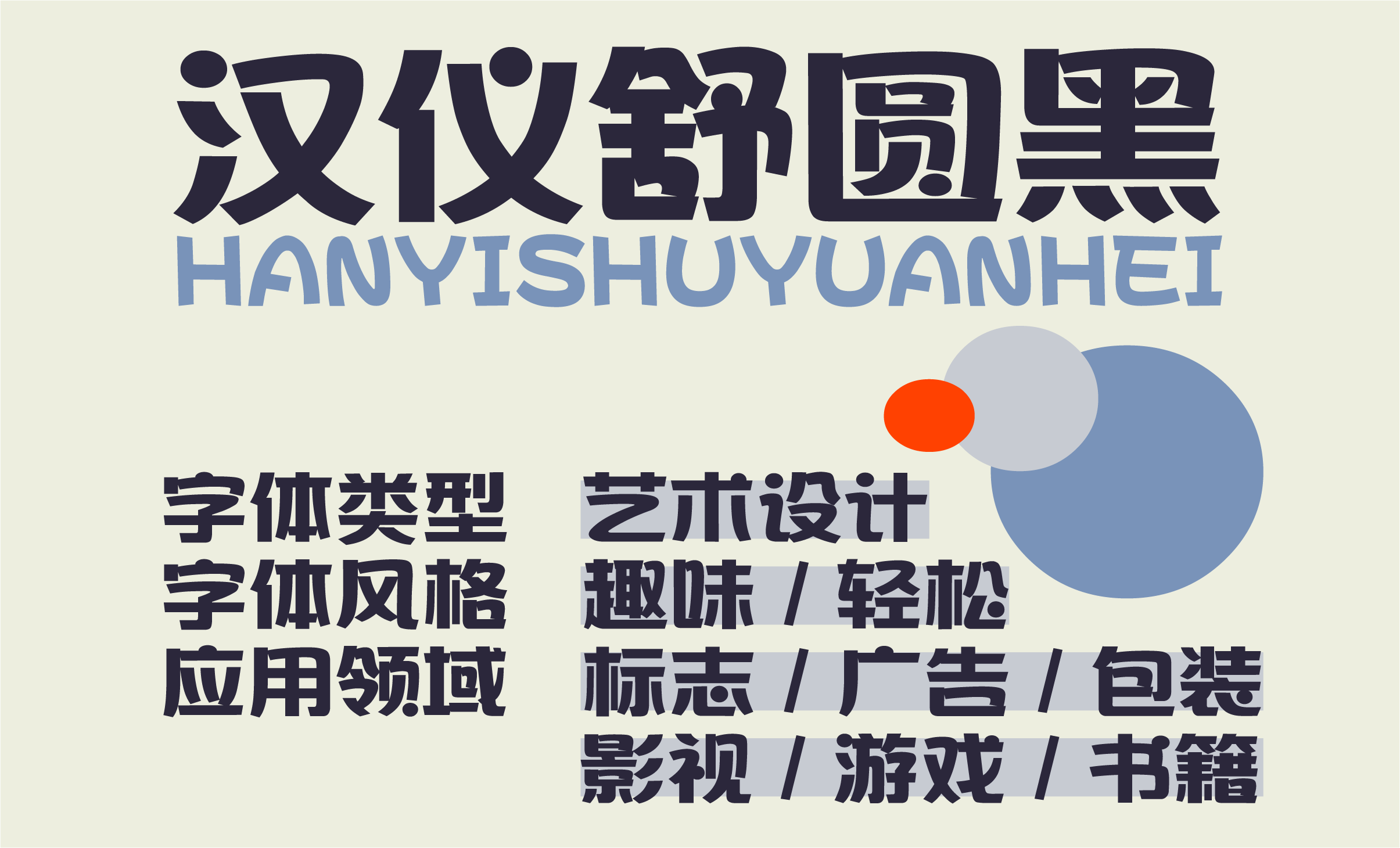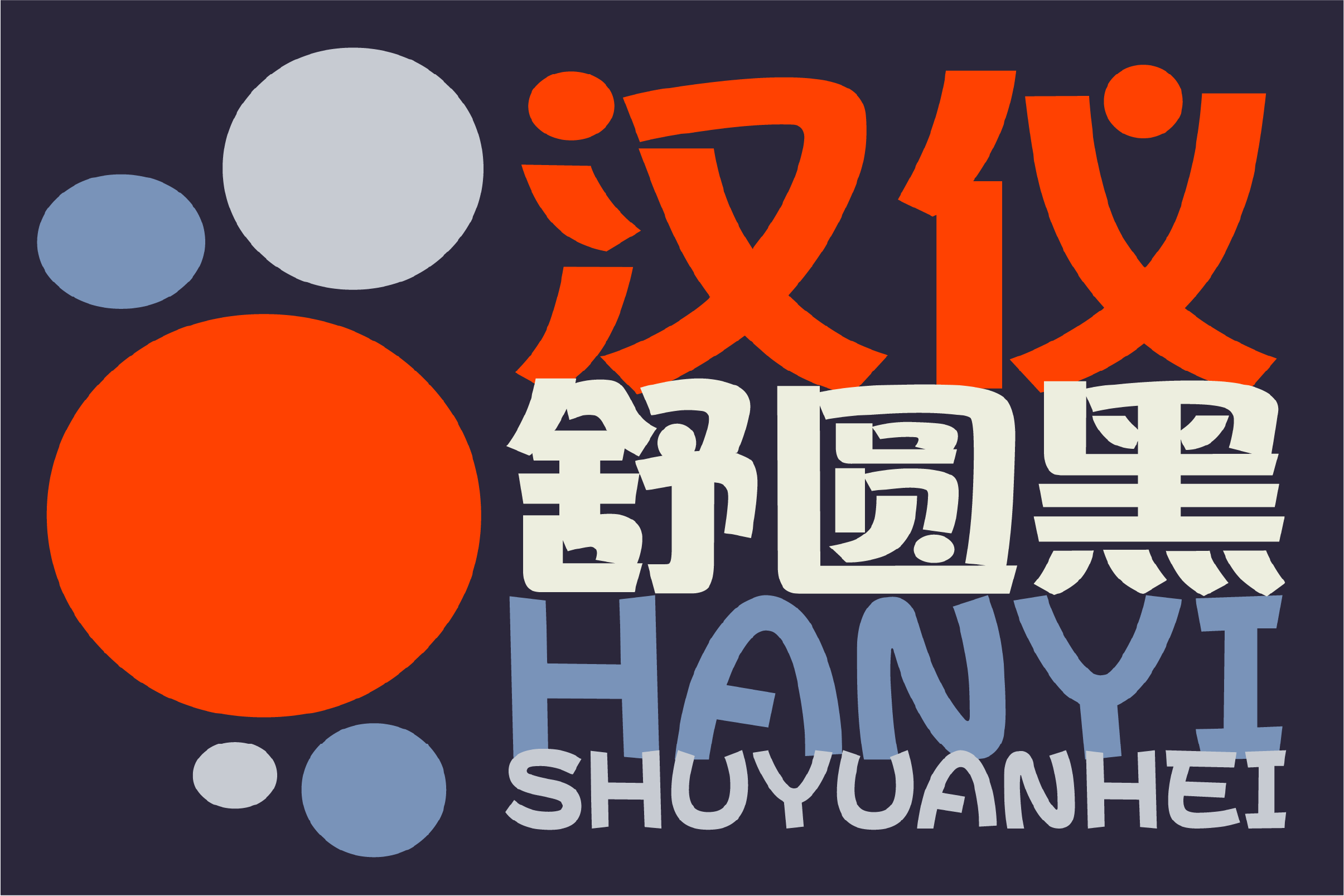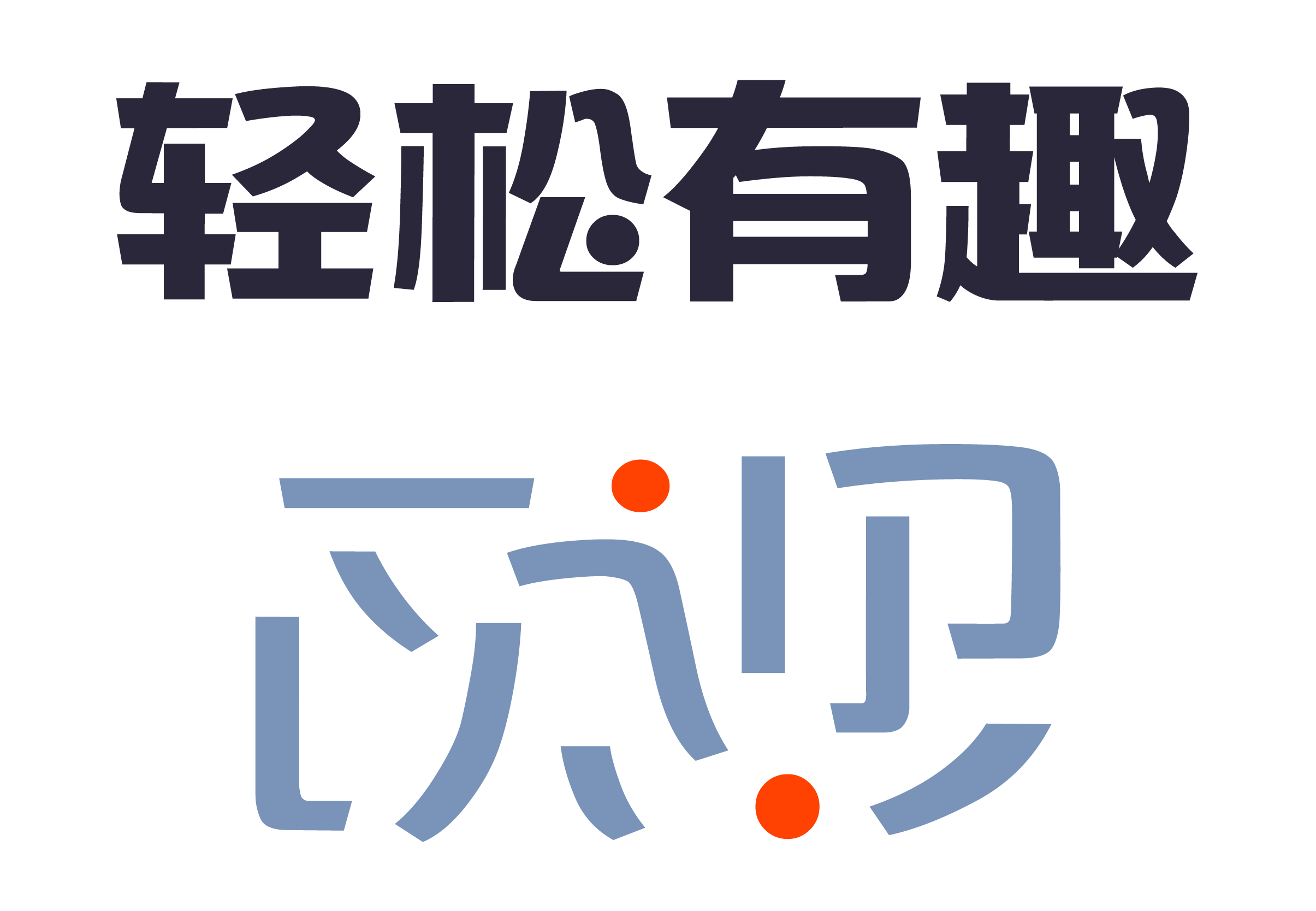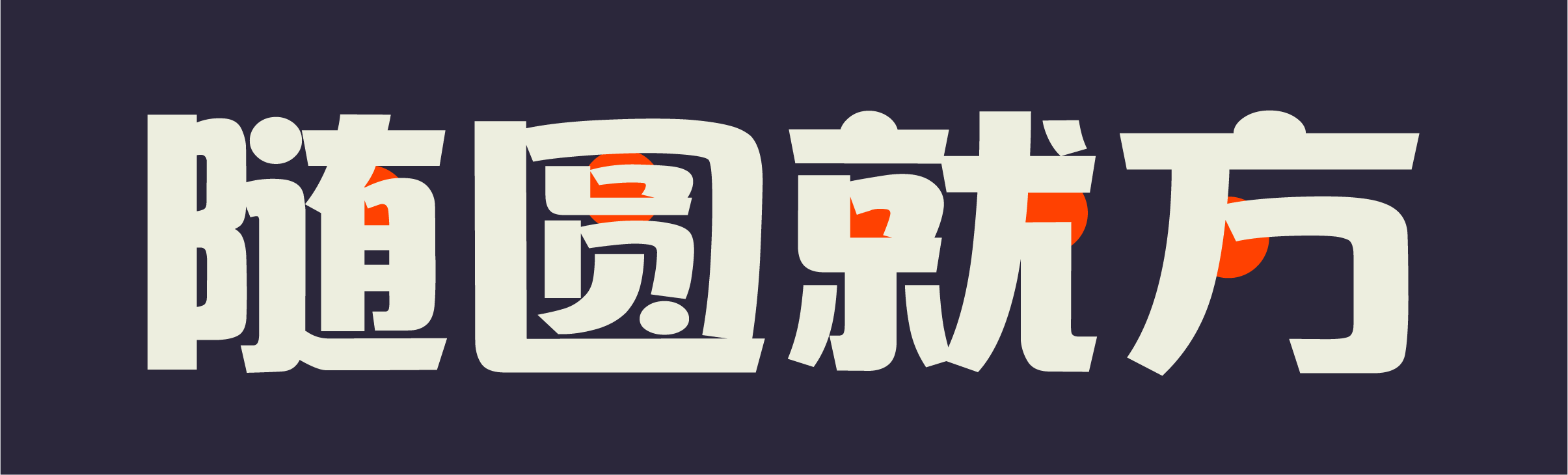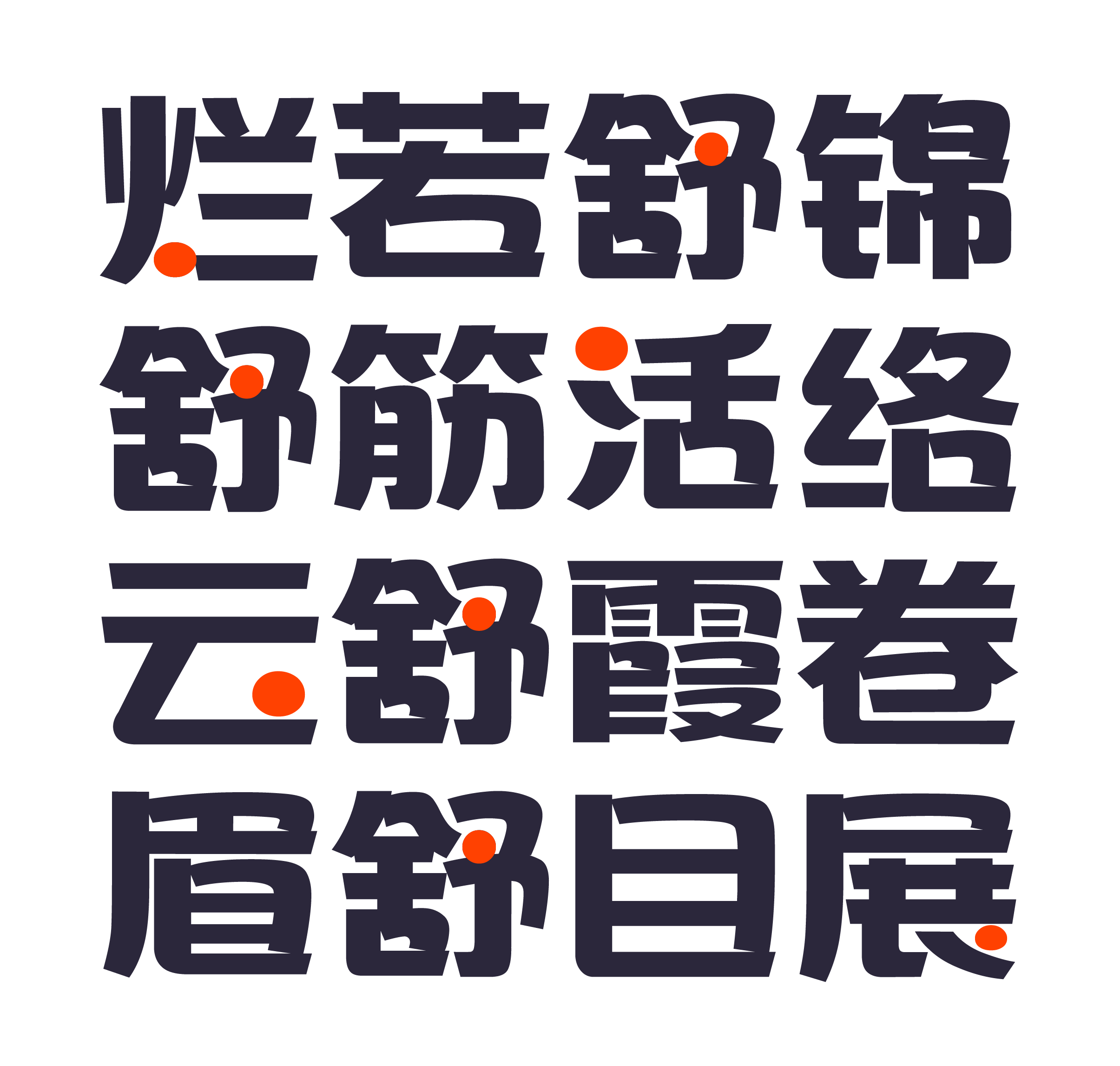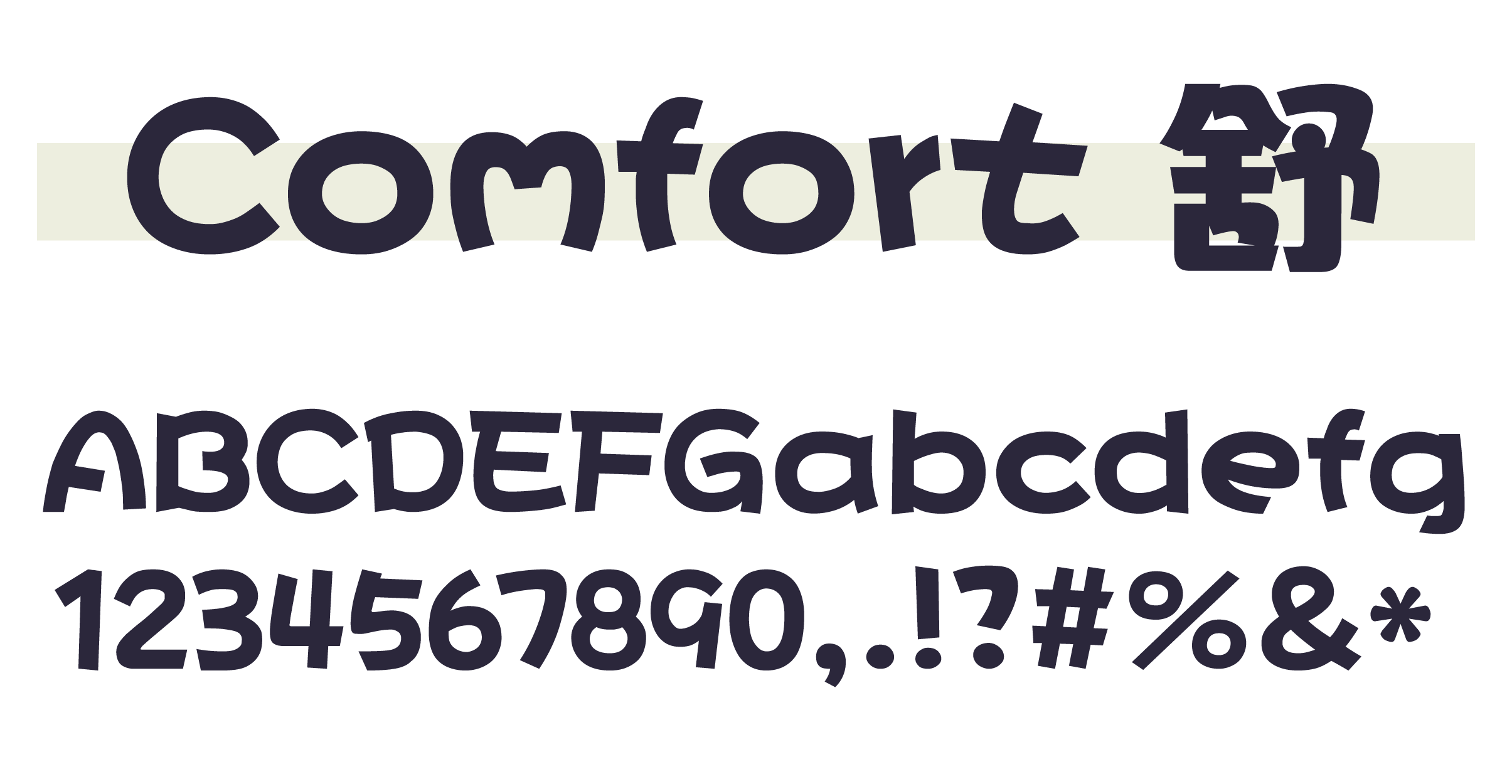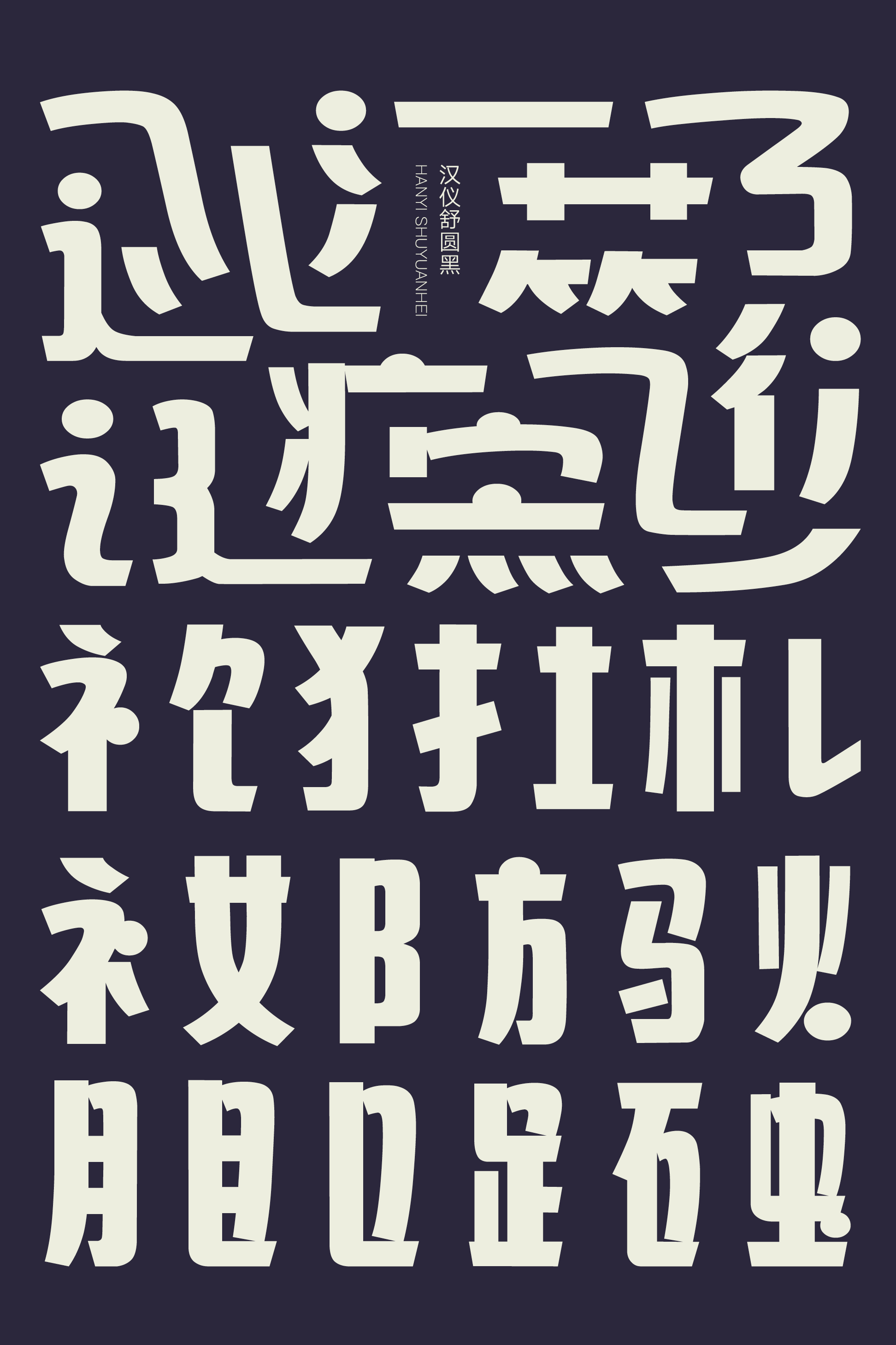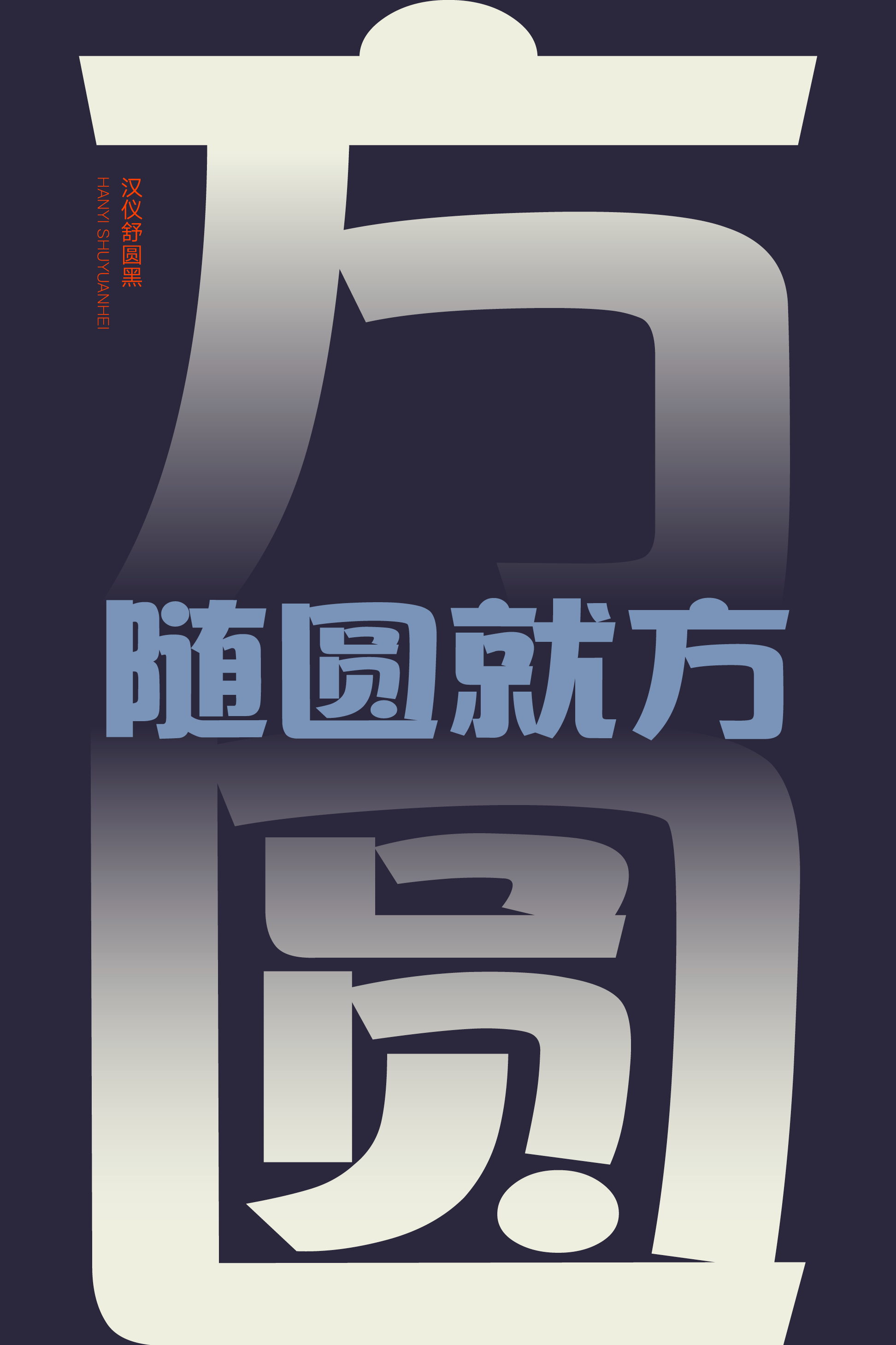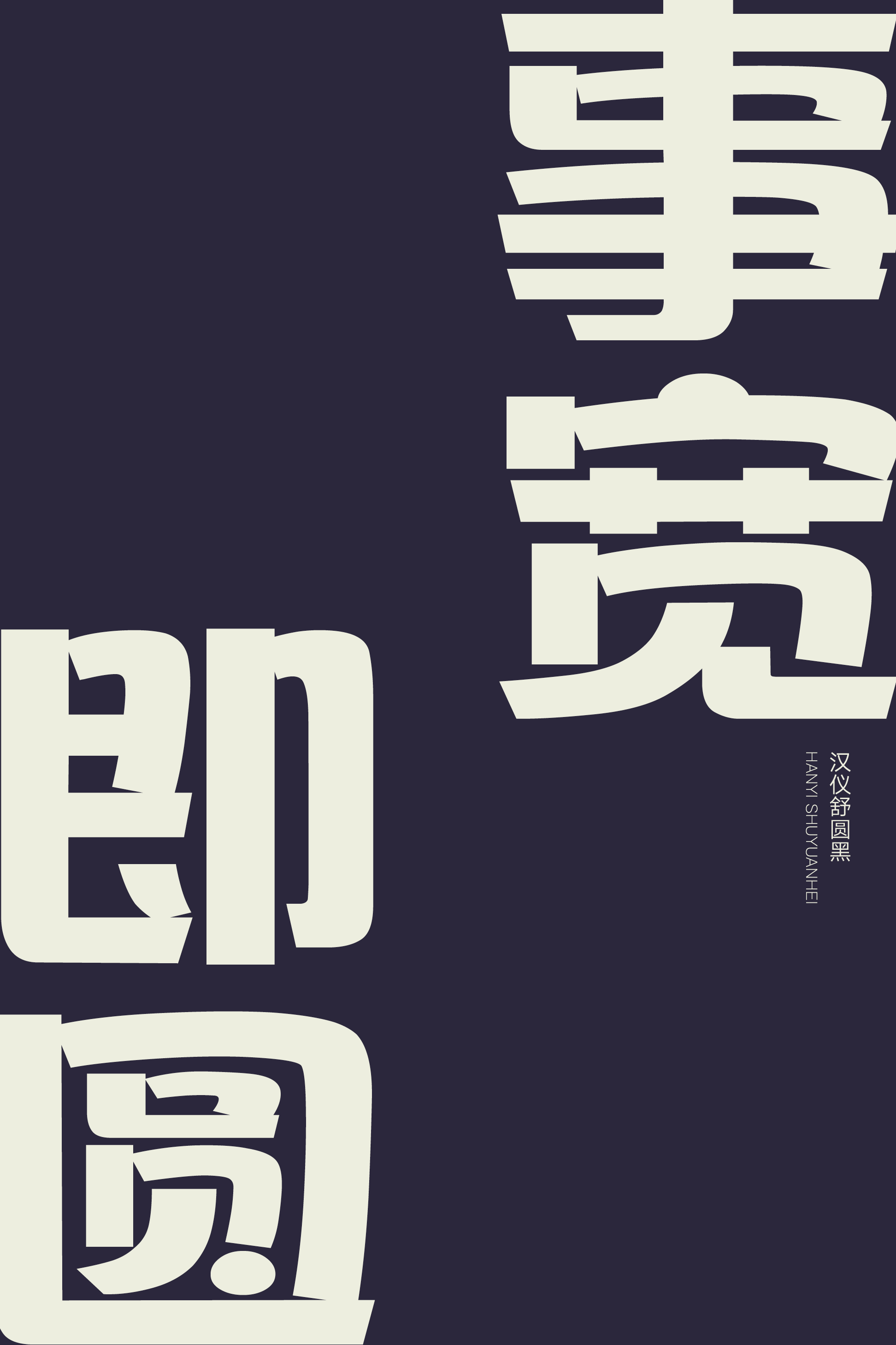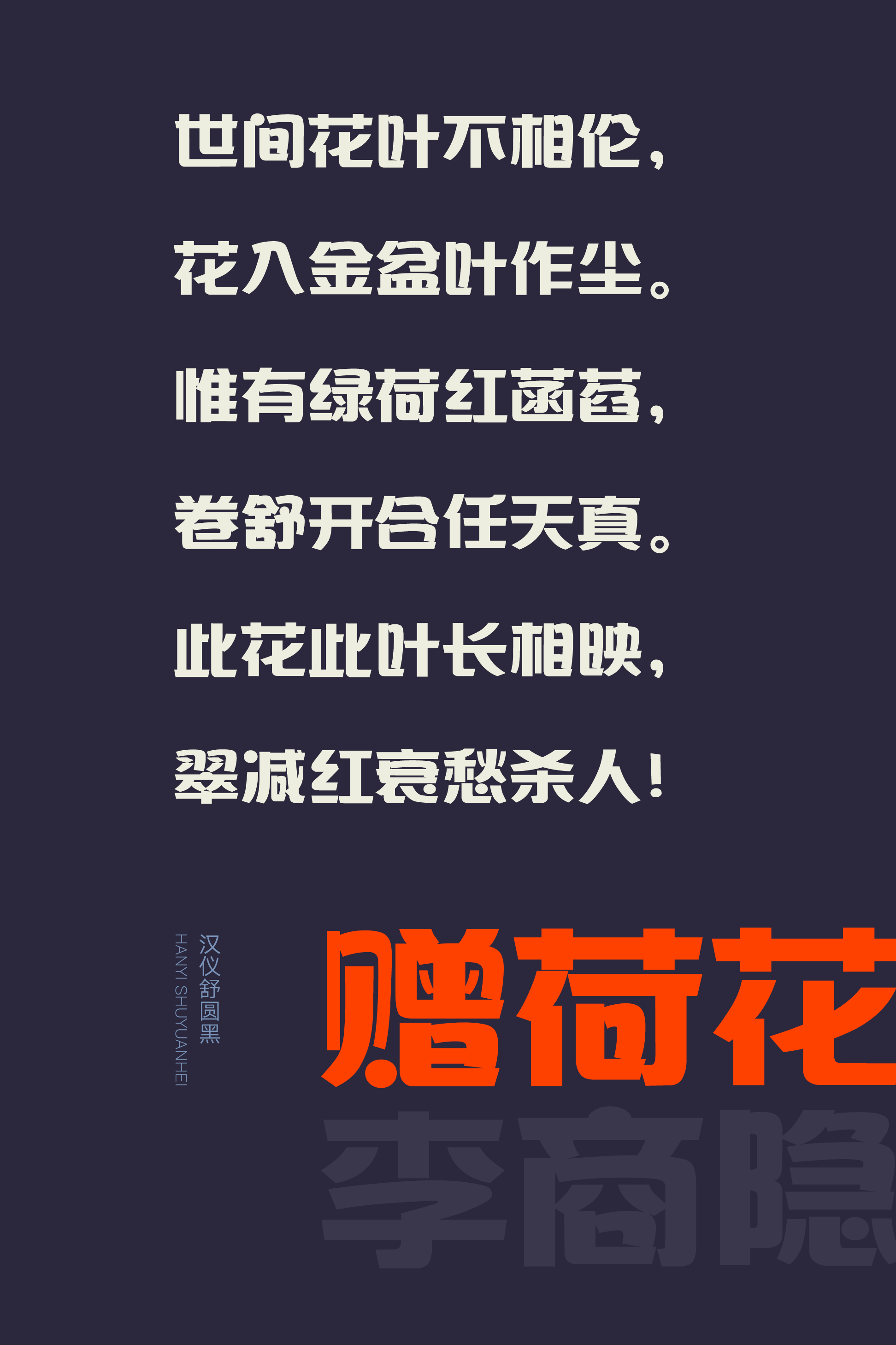
汉仪舒圆黑
舒展的弧线和圆满的点画构成了汉仪舒圆黑,字形扁而饱满,结构舒朗,笔画圆转,笔画线条既有几何的简约,又有手写的轻松。这款细节丰富的标题字体适合用于绘本漫画、影视游戏、产品包装等使用场景,轻松活泼,趣味十足。
字形略扁,重心偏低。
笔画圆转,弧线舒展,带有手写味道。
笔画不完全搭接的处理使整体舒朗。
圆点跳跃其中。
西文部分以同样的线条构成,造型饱满,平稳之中有跃动感。